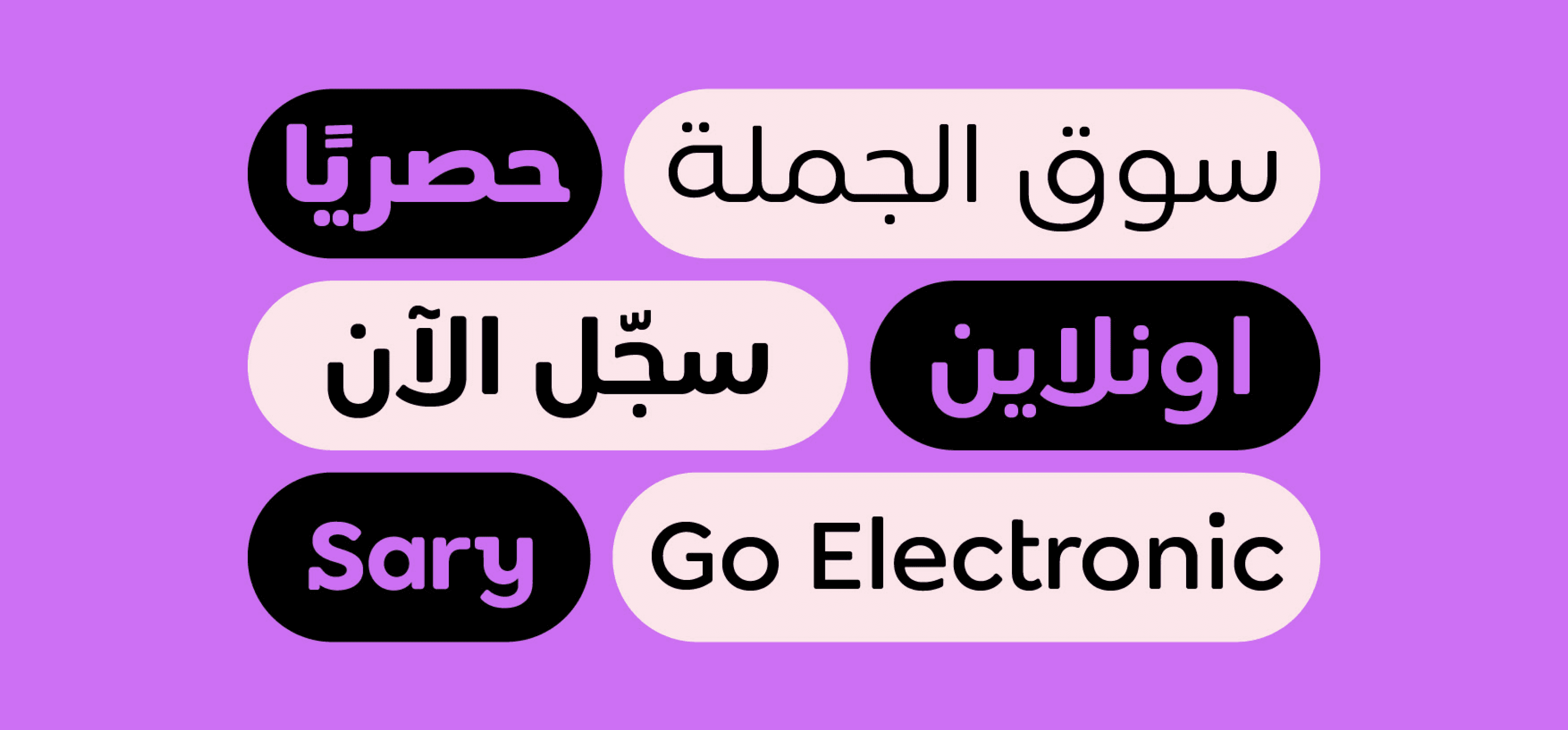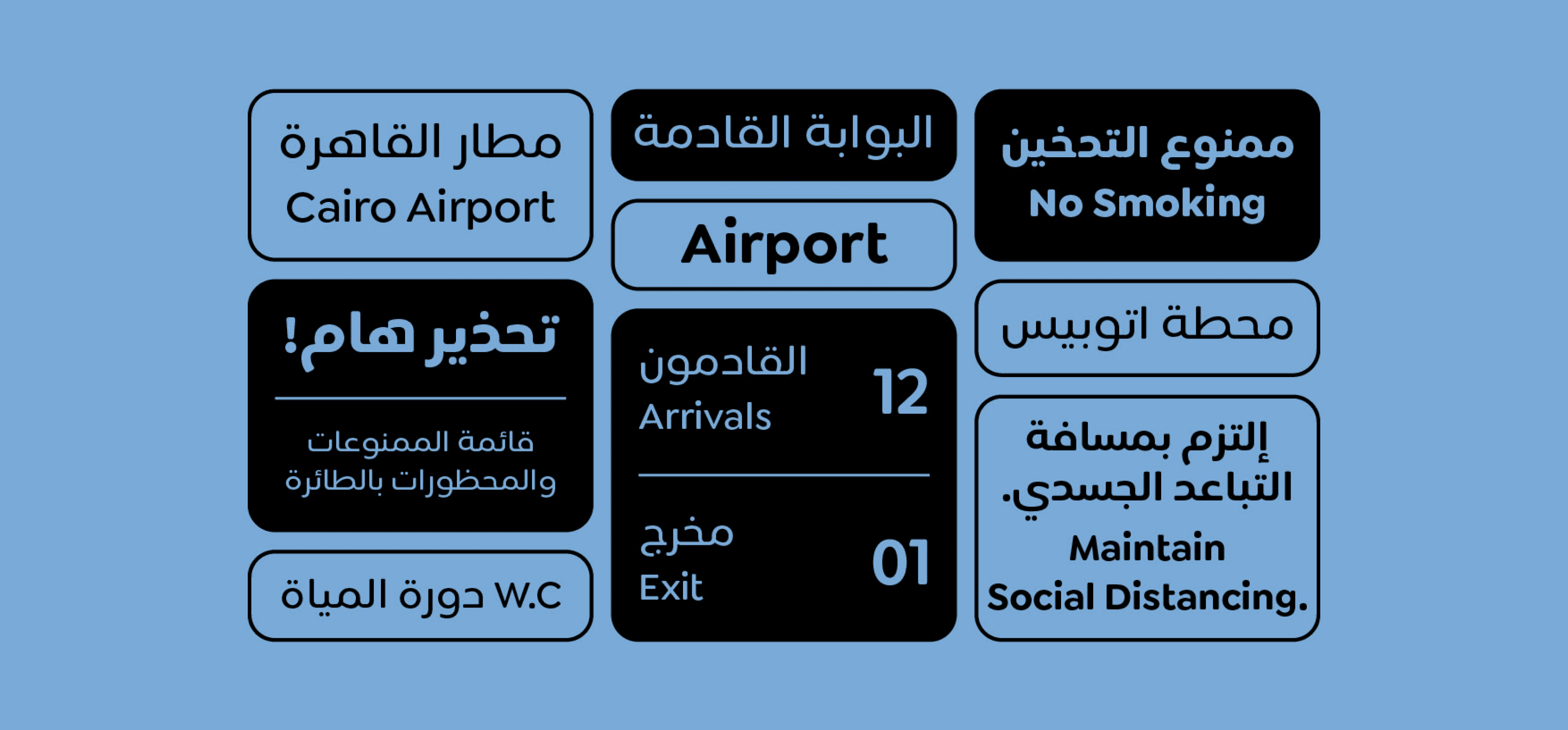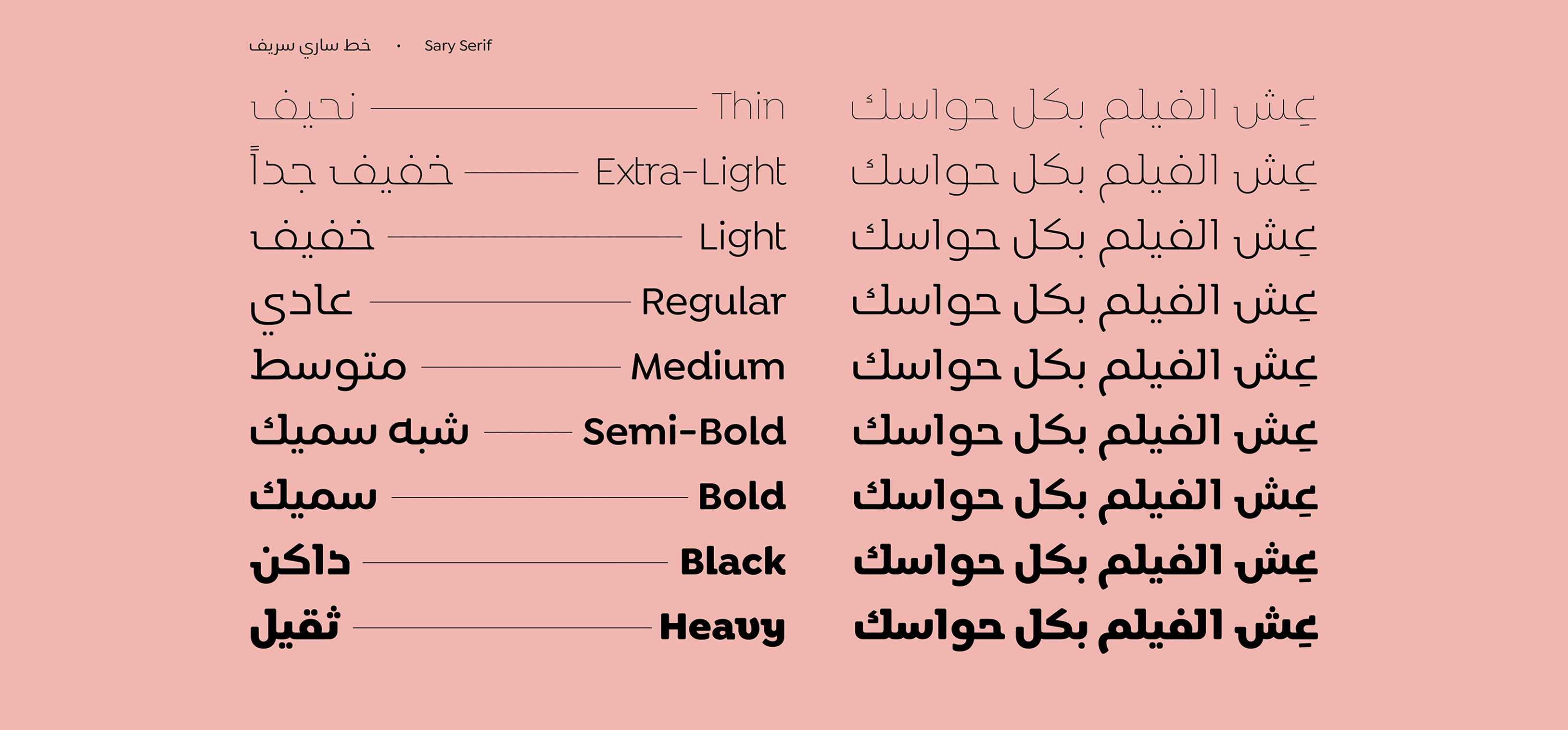
هو خط مخصص لتطبيق "ساري"، ويُعد جزءًا أساسيًا من هوية العلامة التجارية. يتميز بمرونة في الأوزان والأنماط ليتناسب مع استخدامات النصوص الأساسية والعناوين، كما يضم مكتبة كبيرة من الحروف تدعم 91 لغة. صُمم خصيصًا ليعكس شخصية العلامة التجارية بدقة.